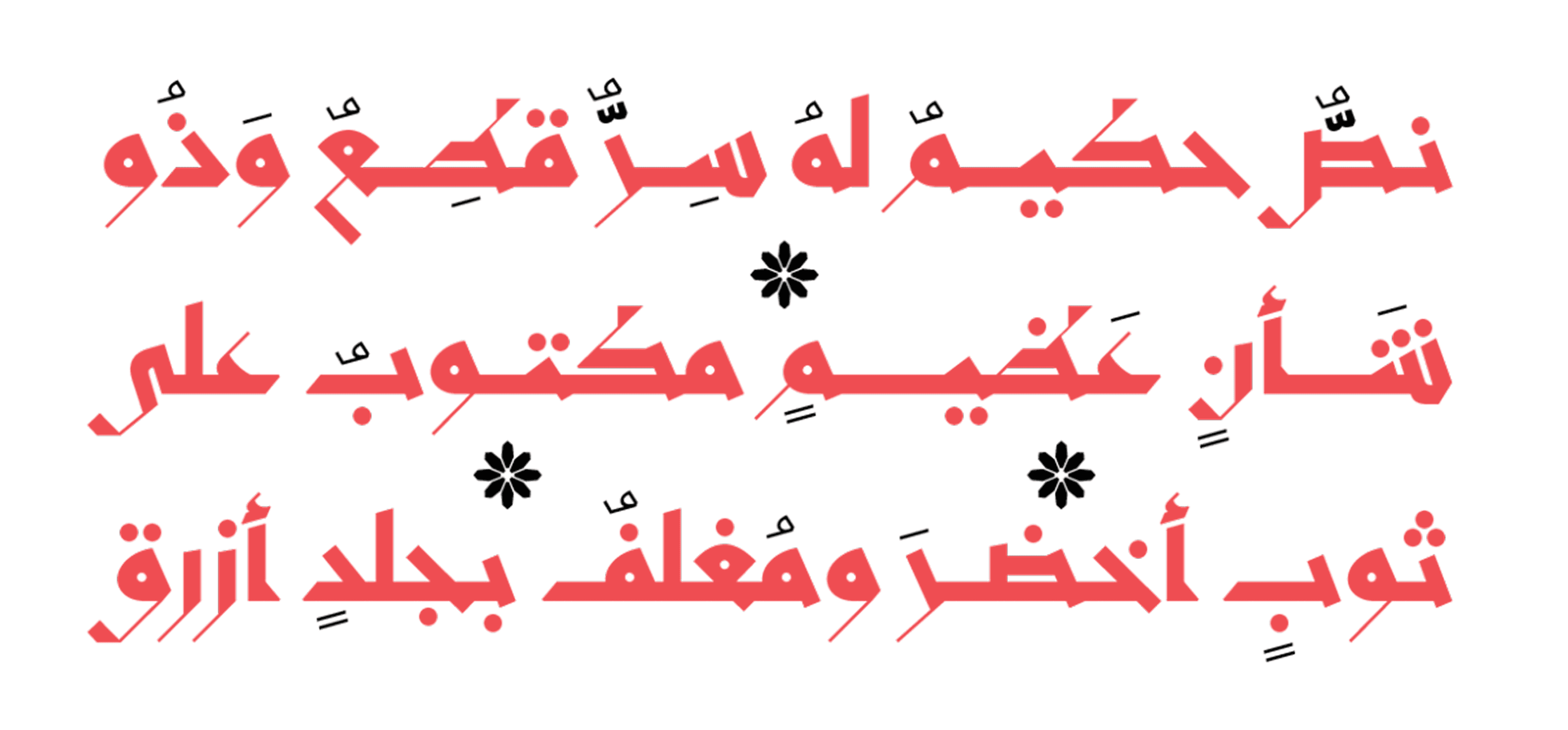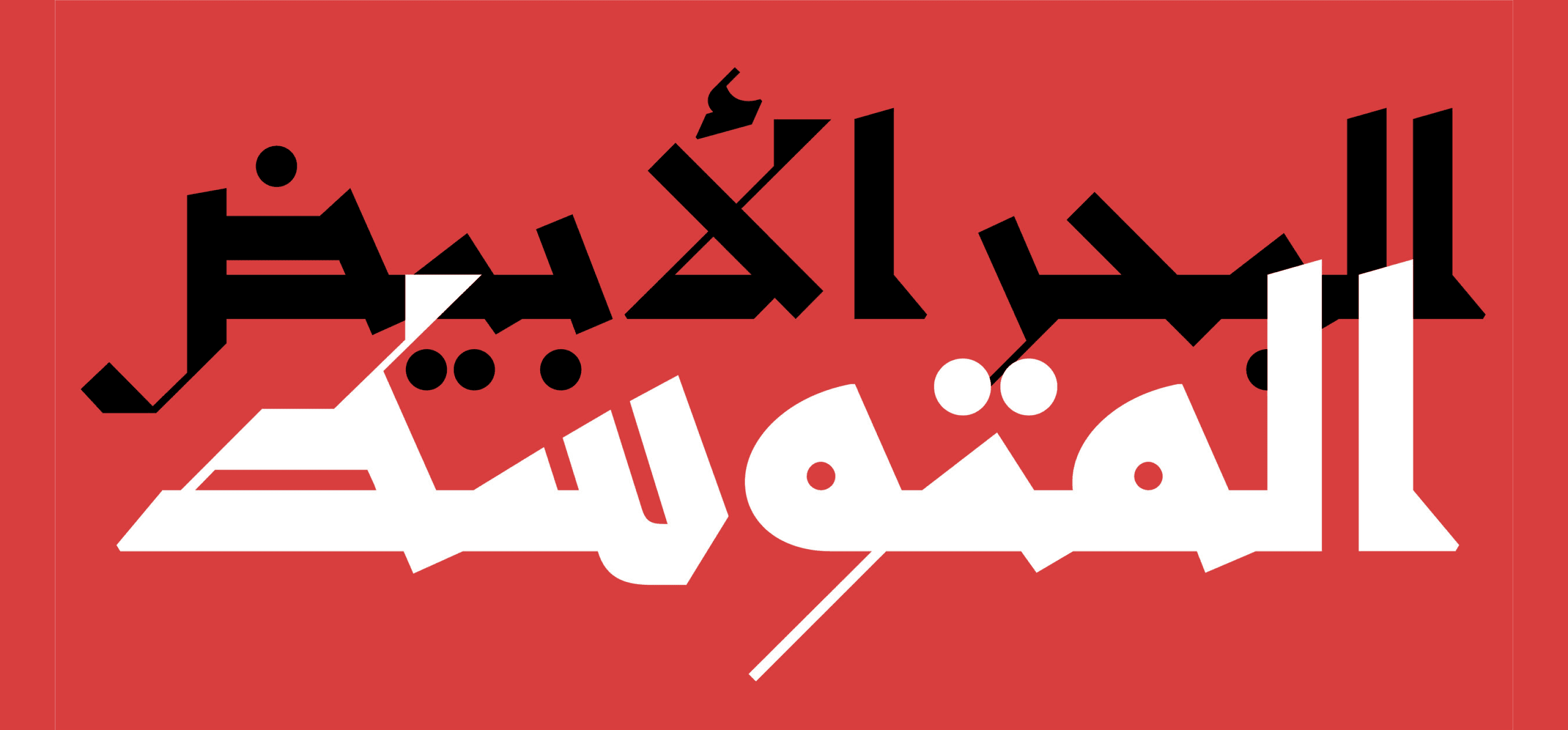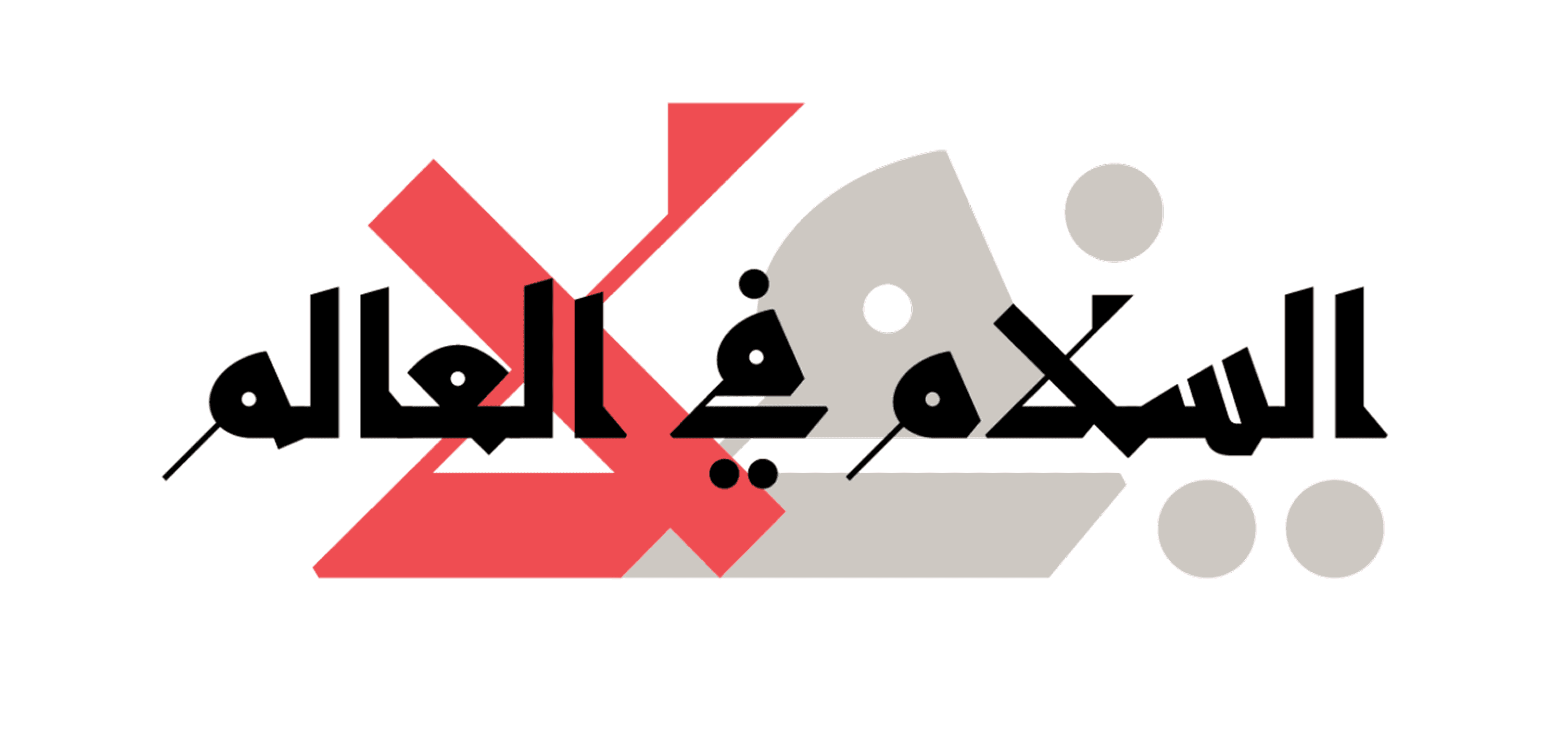
خط أزَل من 29LT هو خط عرضي يتميز بأسلوبٍ هندسي صارم وحواف مائلة قوية تُضفي عليه طابعًا عصريًا جريئًا. يُستخدم بشكل مثالي في العناوين، الشعارات، والهوية البصرية التي تتطلب وضوحًا وقوة تأثير. يعكس الخط مزيجًا بين التراث العربي والطابع الرقمي الحديث، ويأتي بعدة أوزان مرنة تناسب الاستخدامات الطباعية المختلفة.